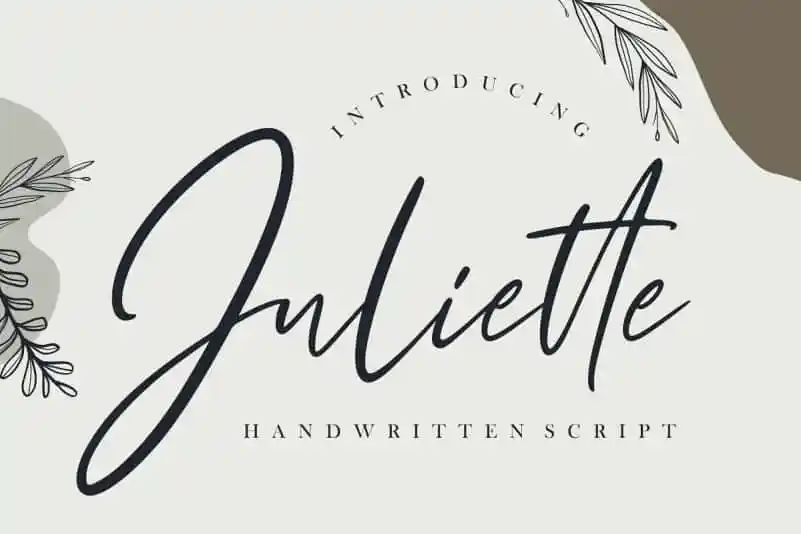
Juliette Script Font – Download Grátis
A fonte Juliette Script é uma elegante tipografia feita especialmente para quem busca texturas agradáveis e fluidas. Com suas linhas suaves e características alinhadas, ela surge como um recurso versátil para designers gráficos. Criada pelo estúdio Creatype Studio, esta font se destaca pela sua flexibilidade em diversas aplicações designográficas. Ela é perfeita para um amplo espectro de projetos que exigem uma pitada de autenticidade na escrita e arte, como marcas de marca, logotipos, designs de casamentos, posts nas redes sociais, anúncios, embalagens de produtos, identidades de produto, rótulos, fotografias, marca d’água, convites e materiais de estação, além de qualquer outra iniciativa que valorize o toque autoral na comunicação visual. Seja para um projeto corporativo ou uma campanha viral nas redes sociais, a Juliette Script é uma escolha ótima para quem busca um toque humano em design gráfico.